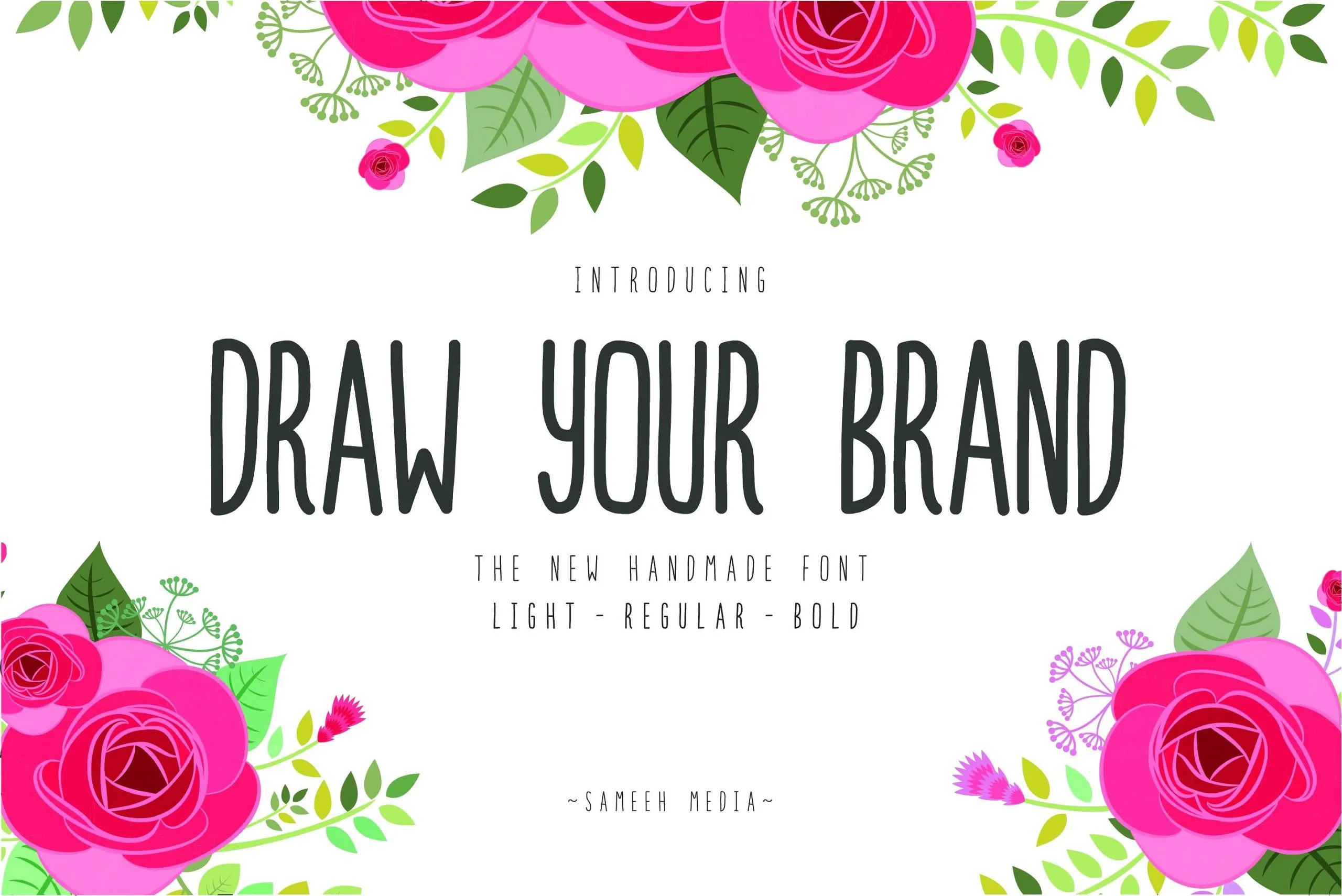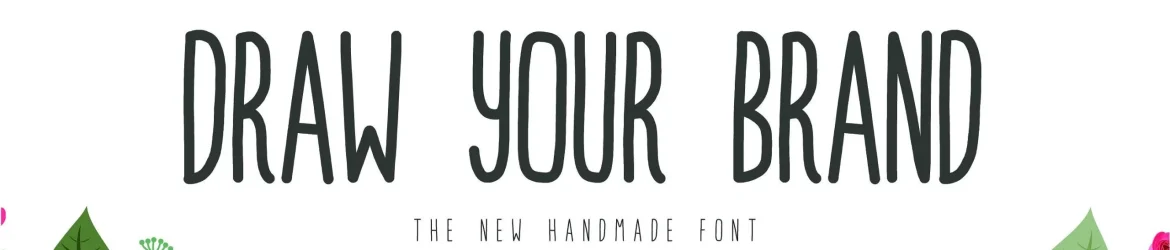
Introduzimos Draw Your Brand Font! Desenvolvido por Sameeh Store, este é um font premium que agora está disponível para download gratuito na CreativeFabrica. O mesmo designer do popular Draw Your Brand também criou esta família de fontes de canetas a mão que permite criar design em letra à mão rapidamente e facilmente. A fonte foi projetada para ser versátil e adaptável, oferecendo-lhe o poder de transformar simples texto em uma arte única e autêntica. Com Draw Your Brand Font, você pode criar designs inovadores e memoráveis sem se preocupar com detalhes técnicos complicados. Para designers gráficos e amantes da arte, esta font não só enriquece seu trabalho, mas também torna a criação de design mais acessível e gratificante. Desfrutar do poder criativo desta fonte pode abrir as portas para uma gama infinita de possibilidades no mundo digital. Estamos ansiosos para vê-lo experimentar o Draw Your Brand Font em suas próprias obras, transformando textos tradicionais em algo que reflete a personalidade única e original do seu projeto.